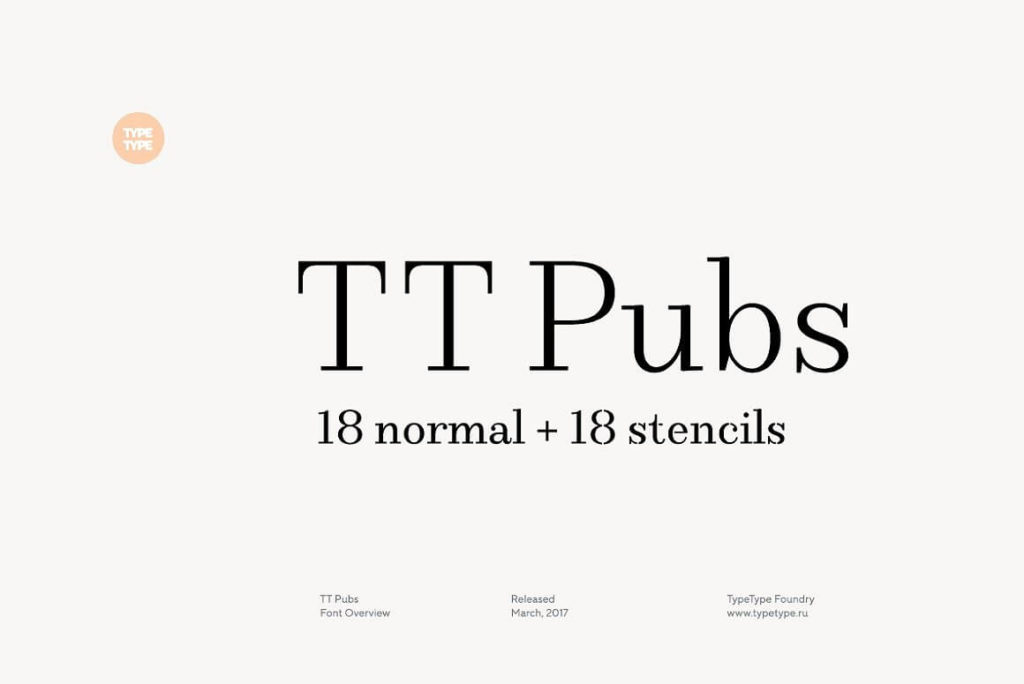
это элегантная антиква с засечками, разработанная Иваном Гладких для студии Typetype в 2017 году. Типографика создана специально для современных экранов и полиграфии, сочетая классическую утонченность с высокой читаемостью. Кириллическая часть гармонично дополняет латиницу: мягкие закругленные засечки (ball terminals) и открытый шрифт придают буквам теплоту и дружелюбие, не теряя профессионализма. Шрифт отлично подходит как для крупных заголовков, так и для набора длинных текстов. Вы можете **скачать TT Pubs бесплатно** на нашем сайте и использовать его в своих проектах